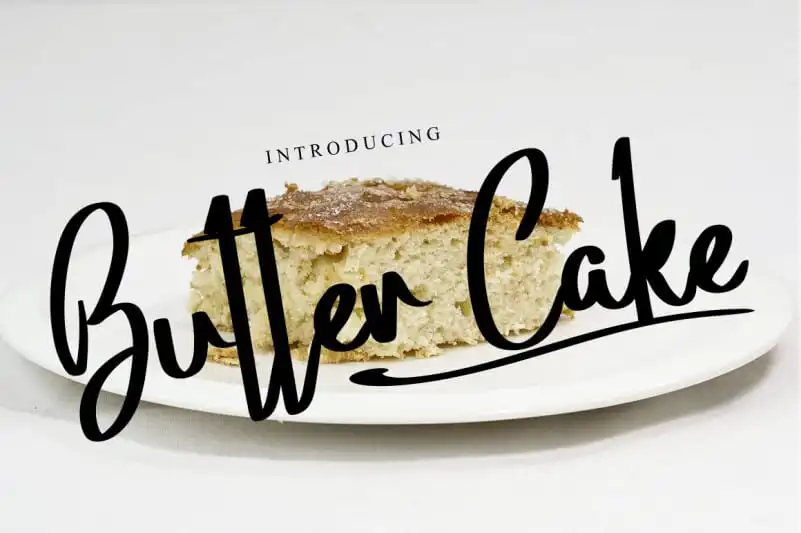
Butter Cake Brush Font – Fonte Grátis
Butter Cake Brush Font
A Butter Cake Brush Font é uma elegante tipografia script, delgada e cursiva, criada para aqueles que procuram uma escrita fluida e suave. Esta fonte, leve e agradável ao olho, combina perfeitamente com diversos projetos de design. Com sua delicadeza e personalidade única, ela adicionará um toque encantador e romântico aos seus trabalhos, tornando-as ainda mais únicas e memoráveis. Este é o ideal para aqueles que buscam uma fonte moderna e sofisticada para dar um toque especial em qualquer projeto de design, desde gráficos até cartões de aniversário ou qualquer outra aplicação visual.